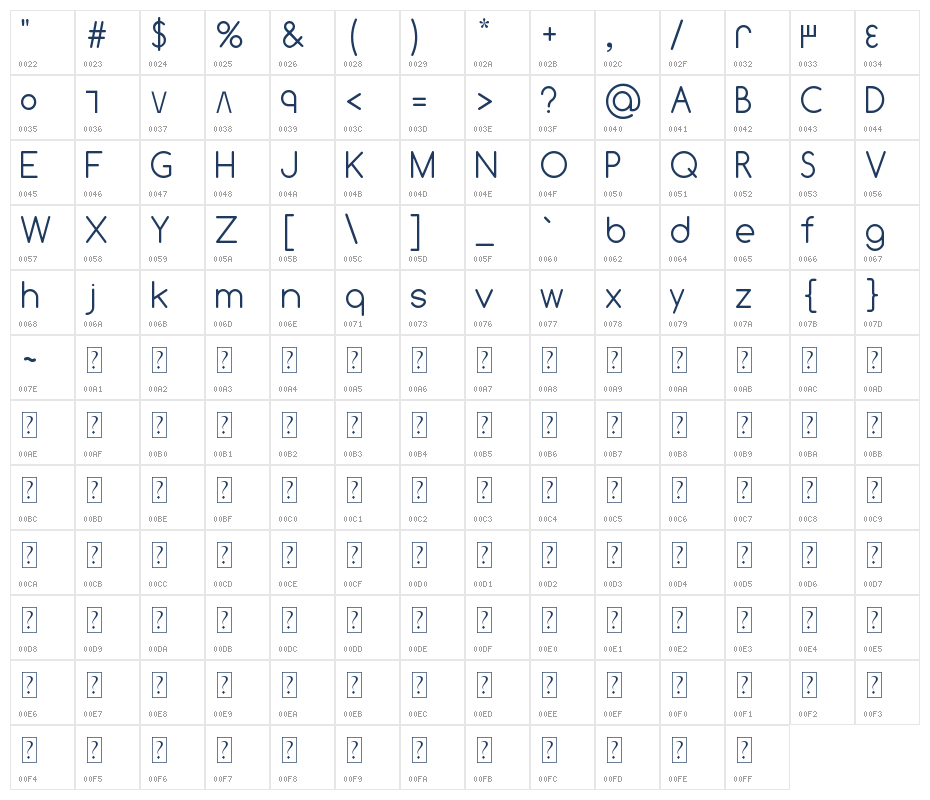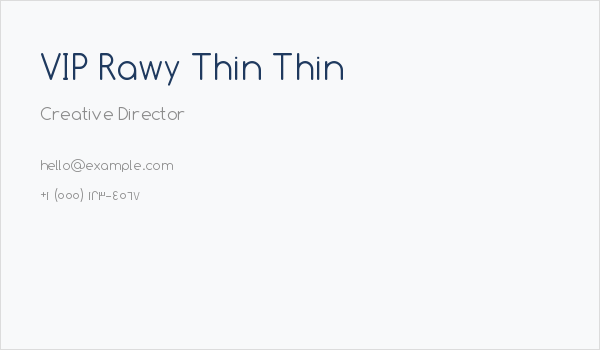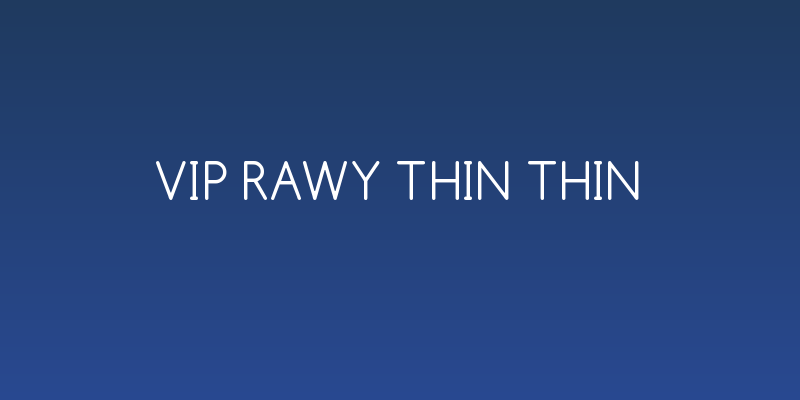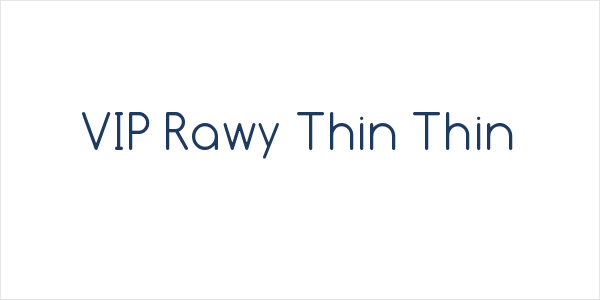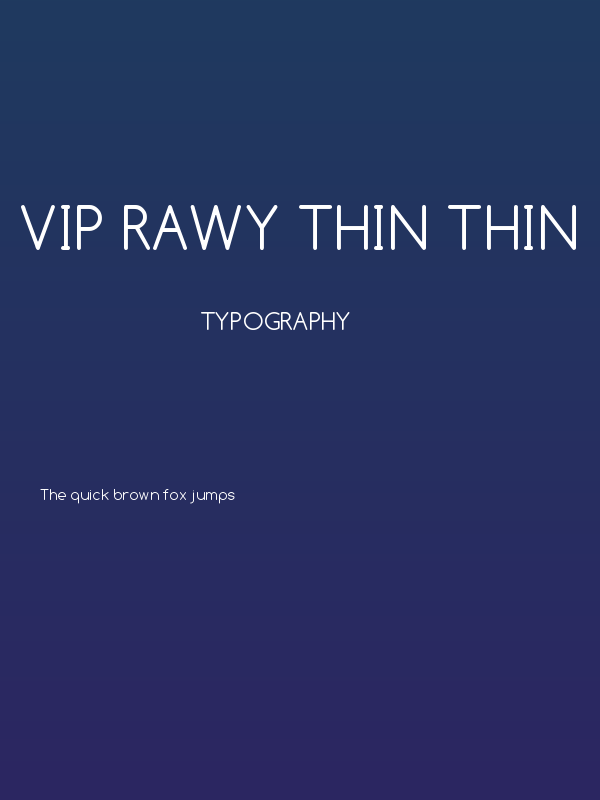
VIP Rawy Thin Thin Font
✎ Round
| Proiecte propuse | Ideal for luxury branding, high-end fashion magazines, minimalist design projects, and elegant invitations. |